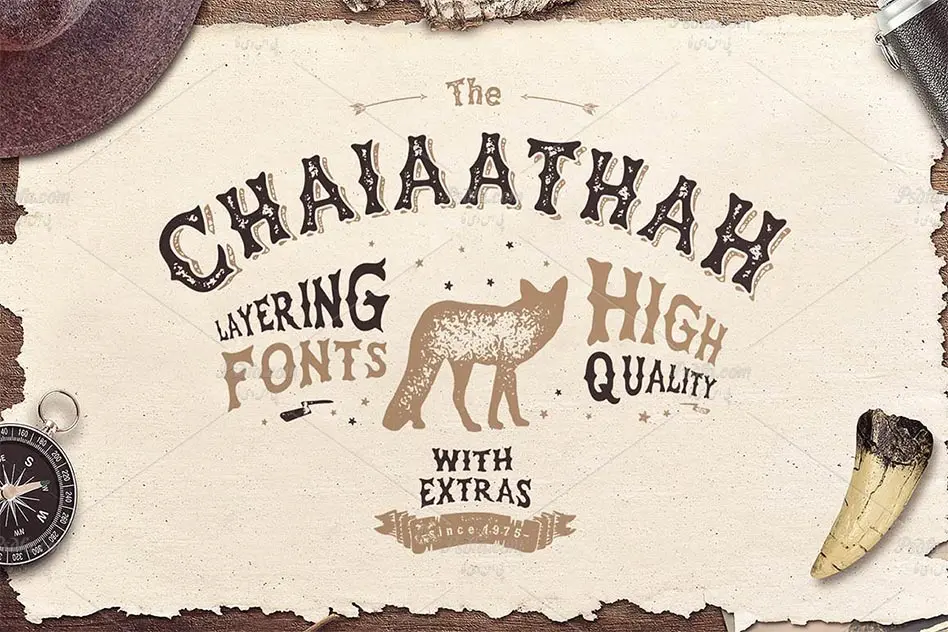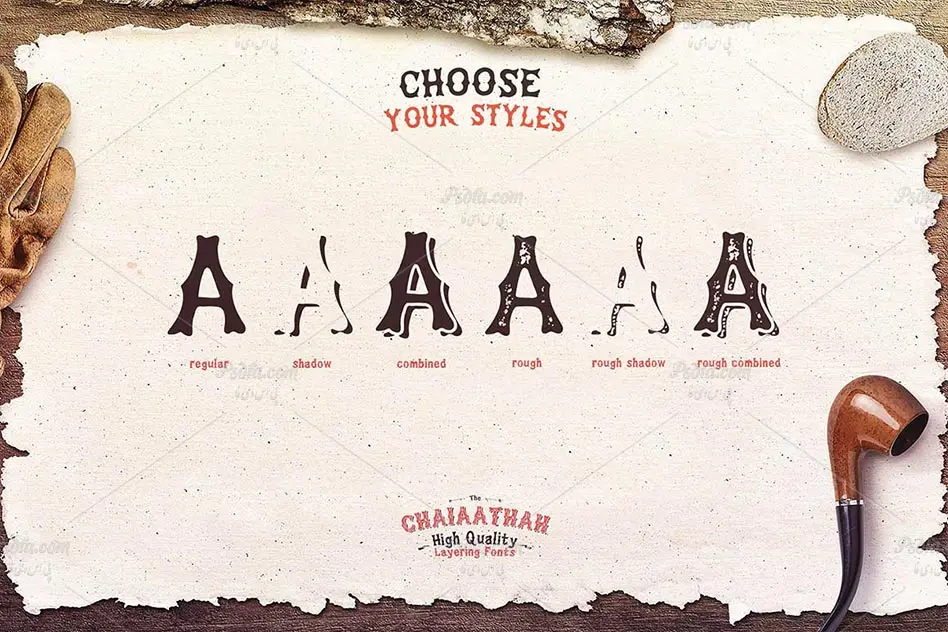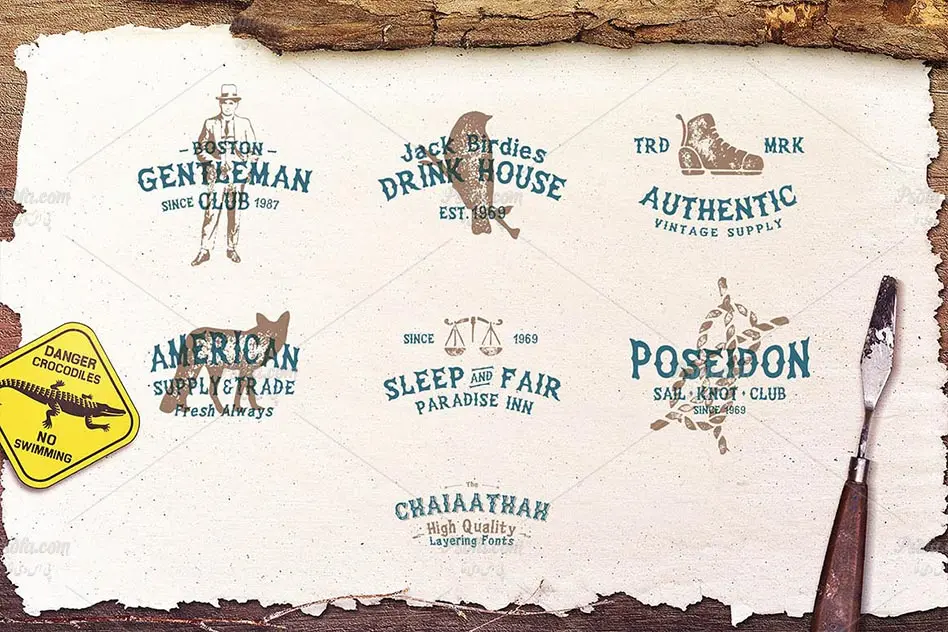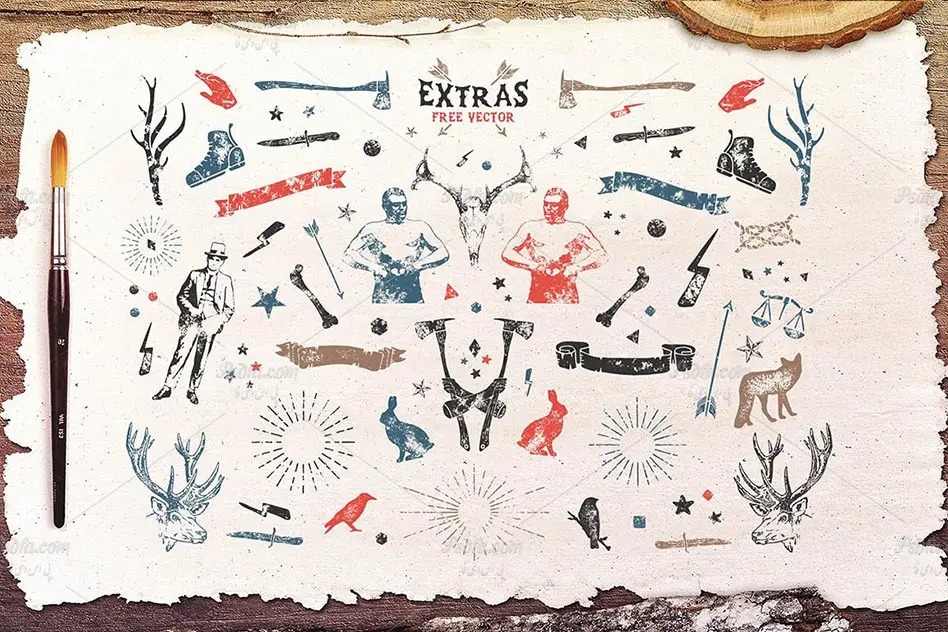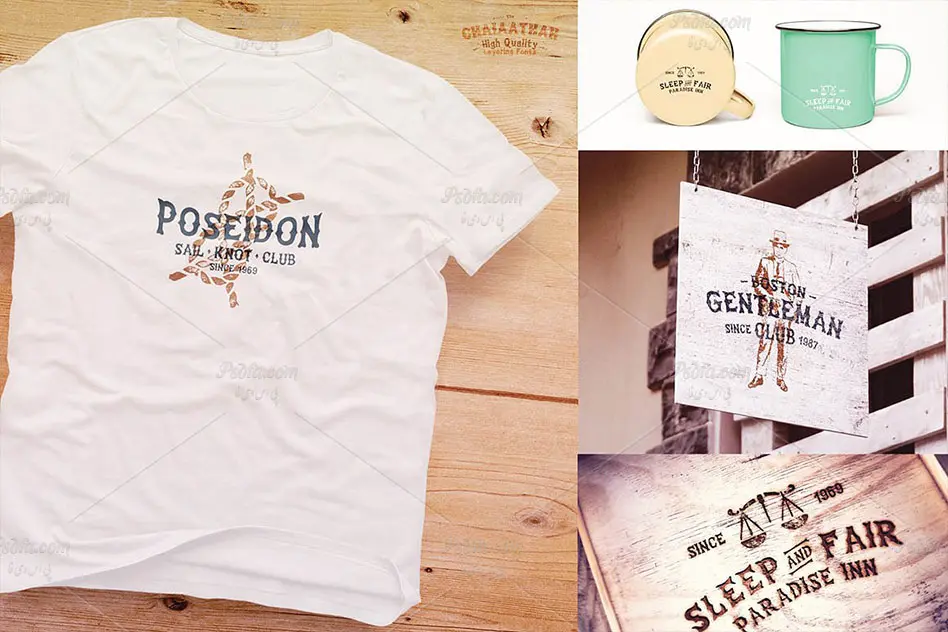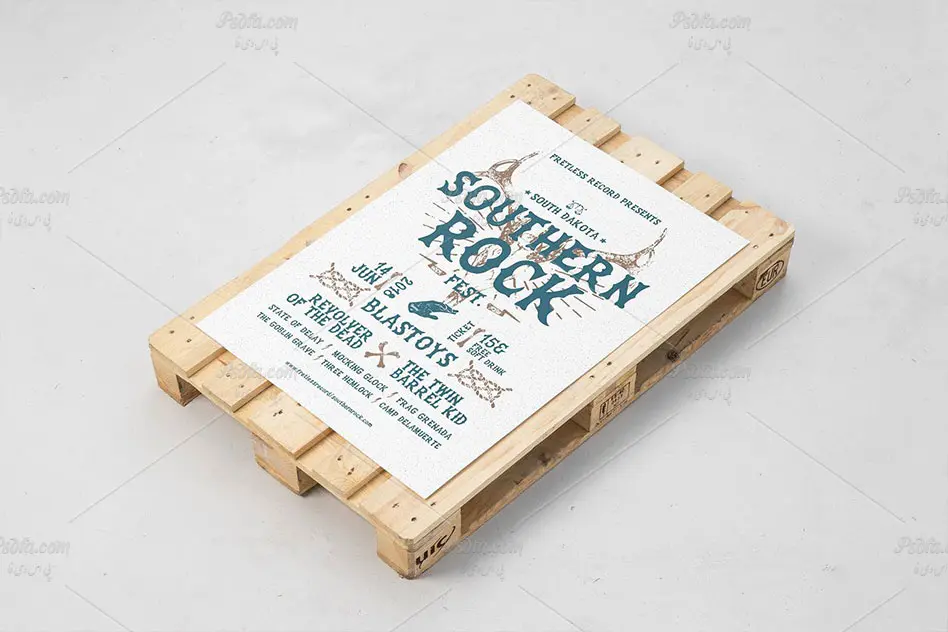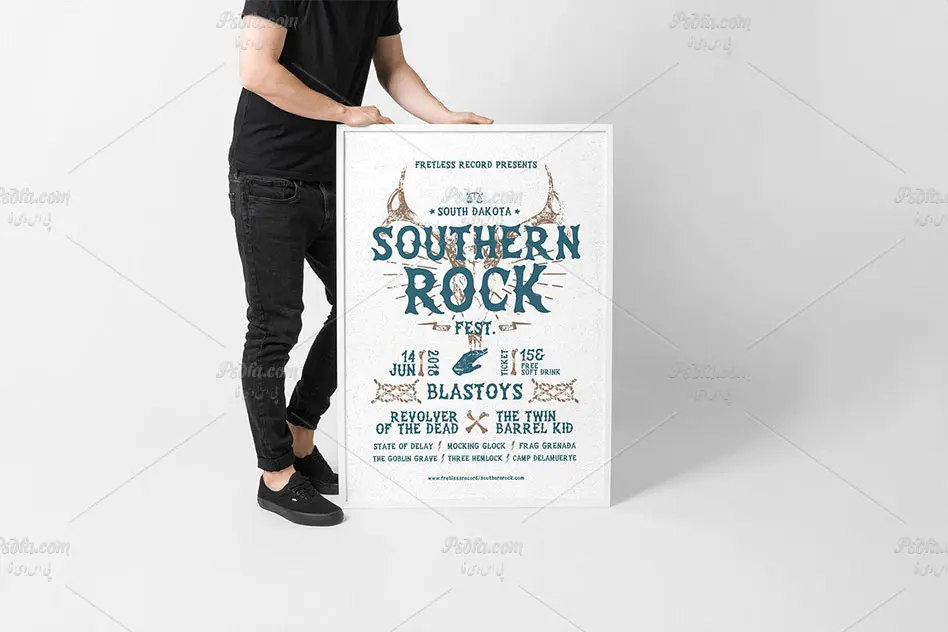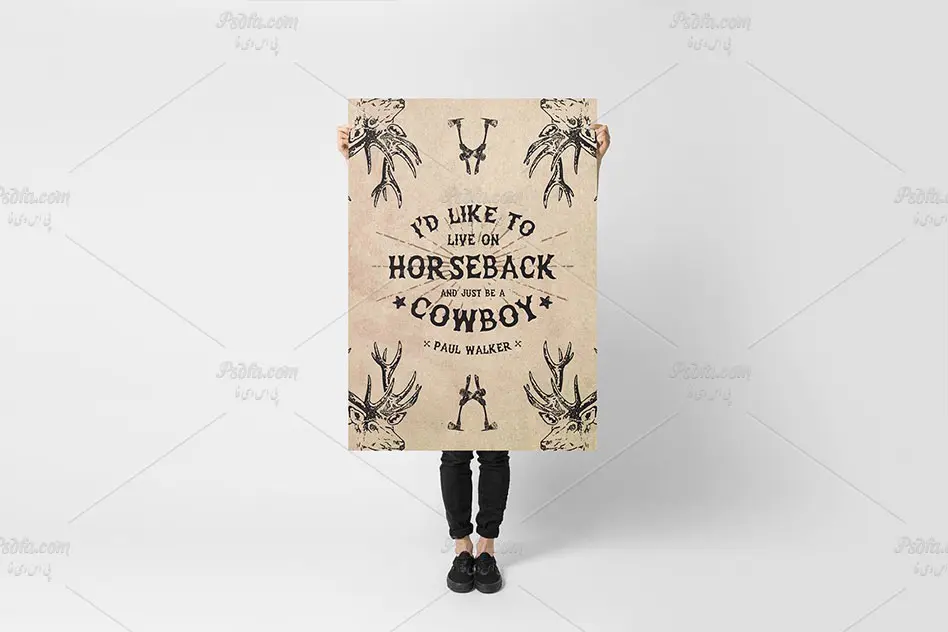
در این مطلب شاهد مجموعه فونت انگلیسی Chaiaathah طراحی شده به سبک فونت های قدیمی غربی می باشید. این مجموعه فونت که از خانواده فونت Chaiaathah می باشد در 6 فرمت otf , ttf , svg , woff , woff2 و otf در سایت قرار داده شده اند که پس از نصب آن ها در پوشه فونت های سیستم می توانید از آن ها به طور مستقیم در تمام نرم افزارهای گرافیکی و ویرایشگر متن از جمله نرم افزار محبوب فتوشاپ ، مجموعه نرم افزار آفیس و … استفاده کنید. همچنین از سایر فرمت های این فونت می توان در طراحی و استایل وب نیز استفاده کرد. مجموعه ای از عناصر تزئینی با فرمت های png و eps نیز در فایل فشرده موجود بوده که می توانید جهت شکل دهی به تصاویر از آن ها استفاده کنید. از این مجموعه فونت می توان در طراحی انواع پوستر ، قاب عکس ، طراحی بسته بندی محصولات ، طراحی بر روی پارچه و لباس و … بهره گرفت.
- کیفیت بالای فونت ها
- 6 حالت مختلف فونت ها
- به همراه عناصر تزئینی